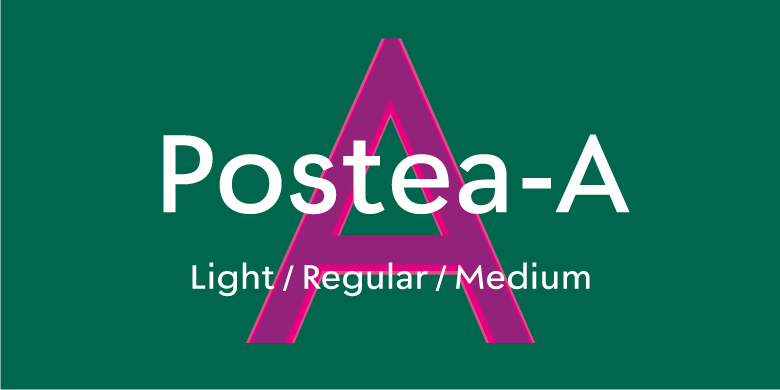
Postea-A
Postea-A,这款字体结构工整、笔画清晰,兼顾美观与易读性,适用于标题、正文、海报、包装、LOGO 等多种场景。字形优雅稳定,风格百搭耐看,适配日常排版与创意设计,让文字呈现更舒适、更具质感。Postea-A一笔一画,皆是细节,以均衡的比例、流畅的线条打造舒适视觉体验,字形端正大气,风格简约现代。无论是商业设计、品牌宣传还是日常排版,都能轻松驾驭,让文字更有格调与力量。Postea-A字体下载。